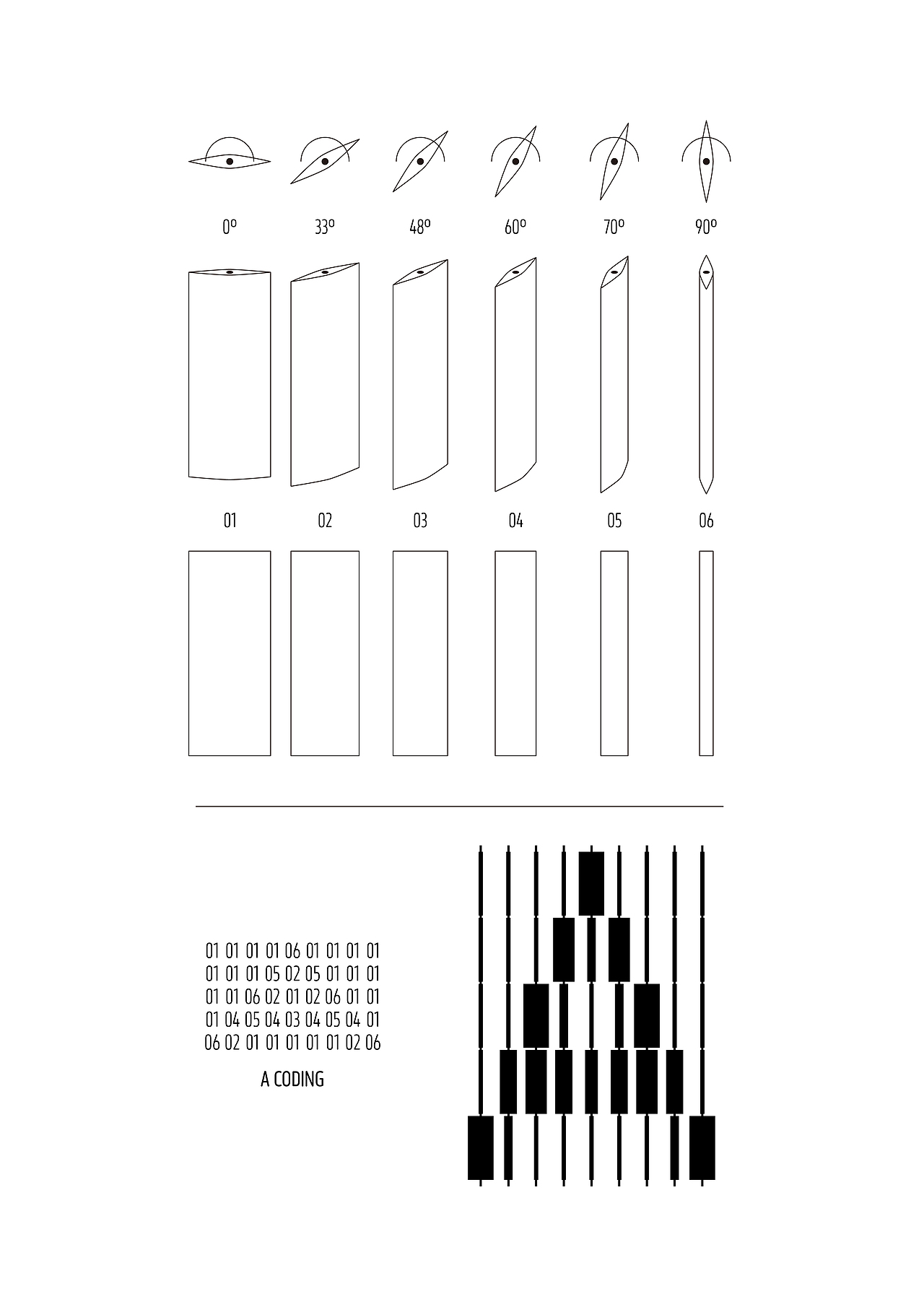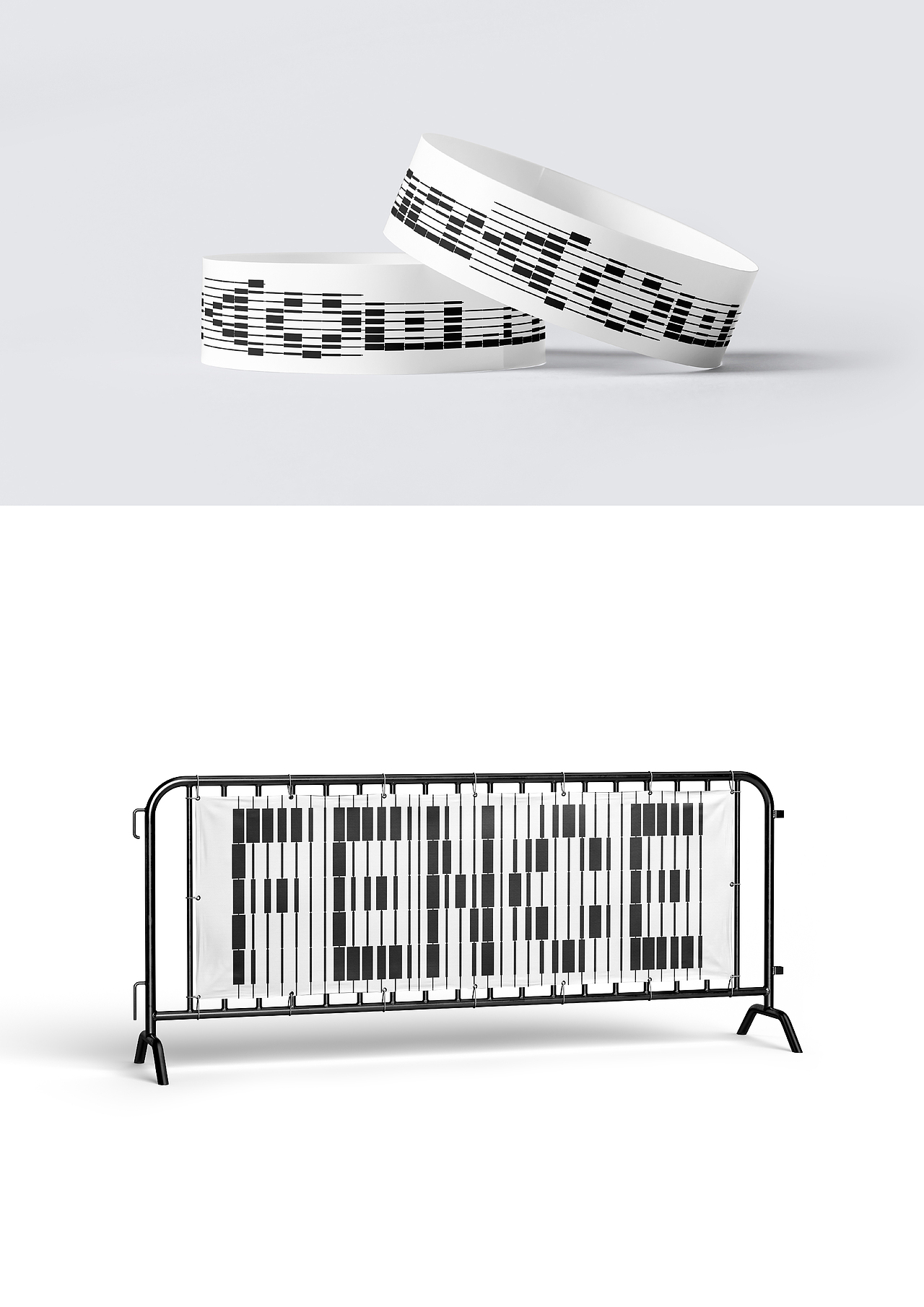
风见体丨风吹一万次总能见到你的名字
实验字体 风见体
为一套装置做的一套字体
每一根竖轴固定五片可以旋转的叶片,每次有风吹过叶片就会随机的旋转角度,呈现出随机的疏密关系,随机的出现不同的图案或者文字(当然可以手动整)
一只猴子用无限的时间,敲击打字机,总能敲出一本莎士比亚
风吹一万次我总能见到你的名字